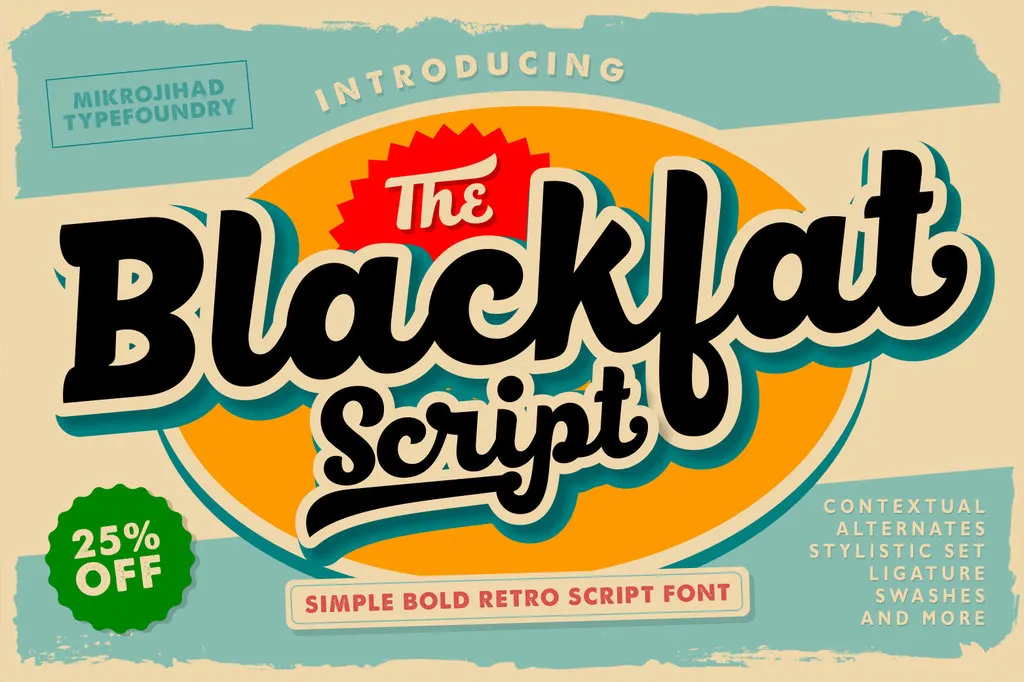
Introduzimos The Blackfat Script, uma nova fonte script afetiva e bold com toques retro. Inspirada nos estilos do passado, esta fonte se destaca pela sua expressividade e personalidade inconfundível. Criada pelo talentoso designer Hamilton, The Blackfat Script traz consigo um charme sofisticado que se adapta perfeitamente a títulos de grande porte ou textos mais detalhados. Perfeita para projetos em estilo vintage ou para adicionar um toque moderno e único aos seus designs, esta fonte é uma excelente escolha para quem procura um grau de sofisticação que se mistura com uma pitada de nostalgia. Não perca a chance de trazer vida às suas criações digitais através desta nova opção de tipo The Blackfat Script.